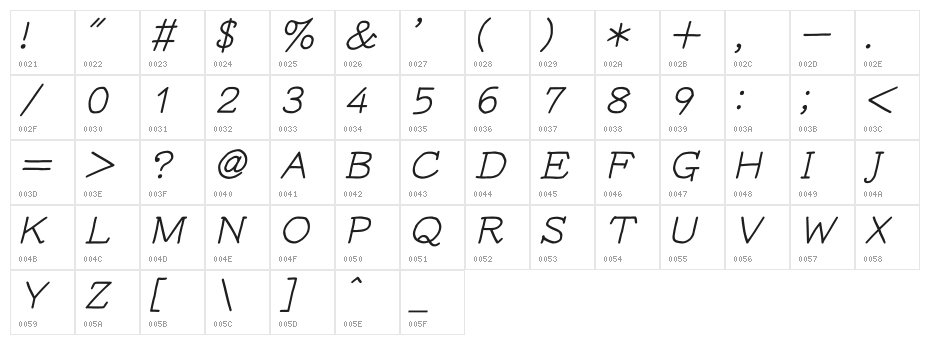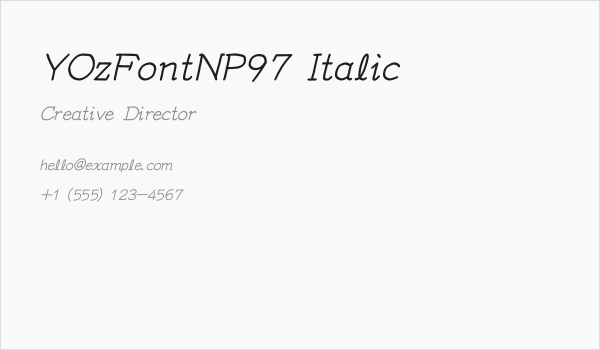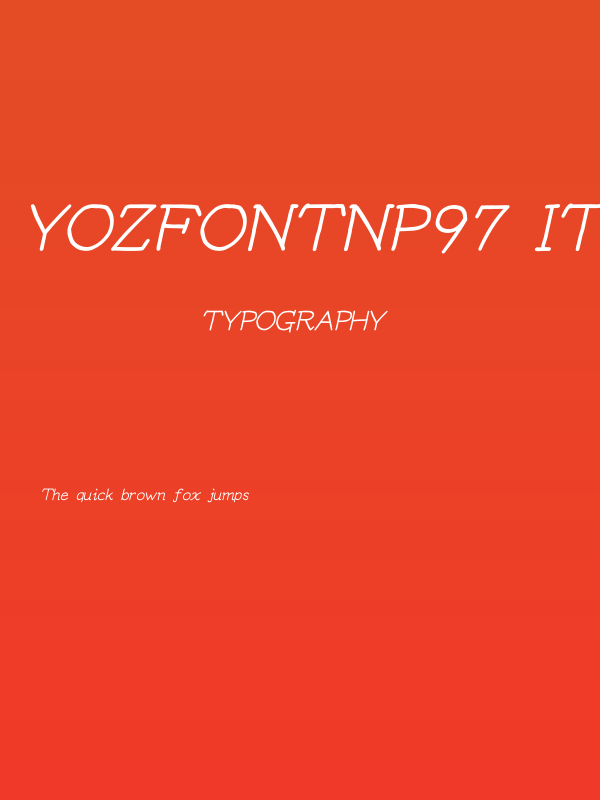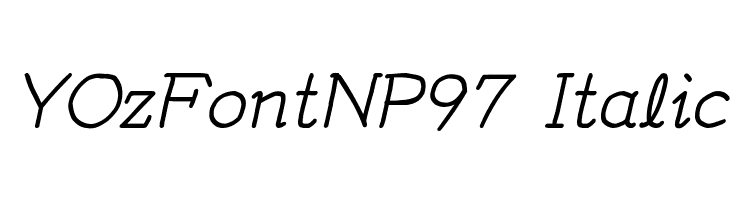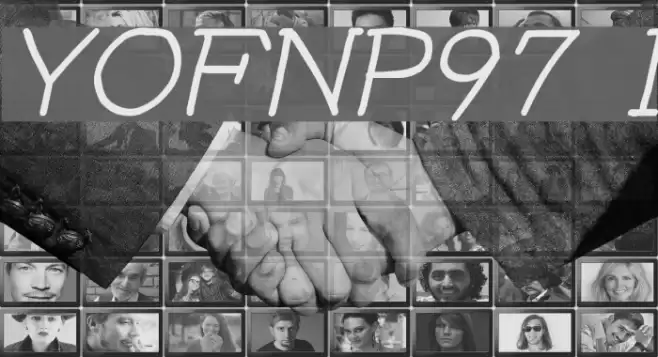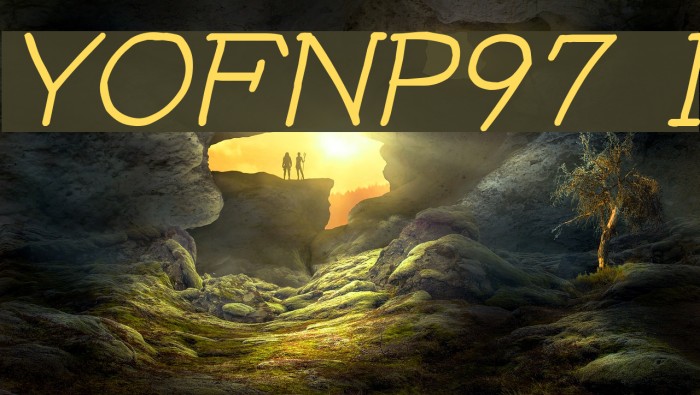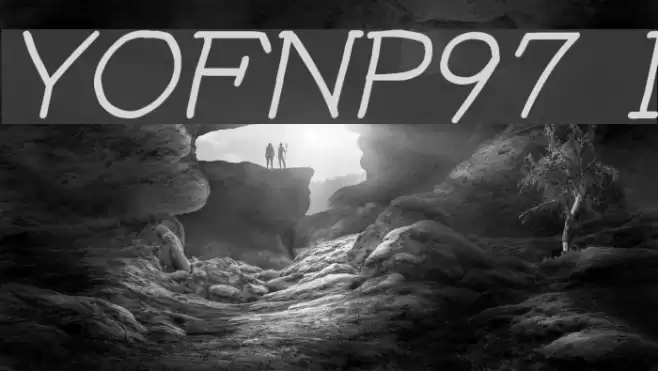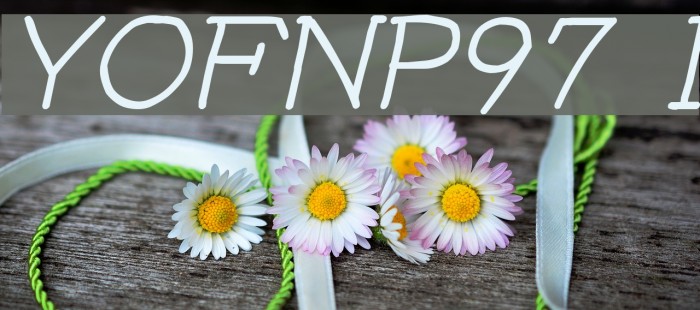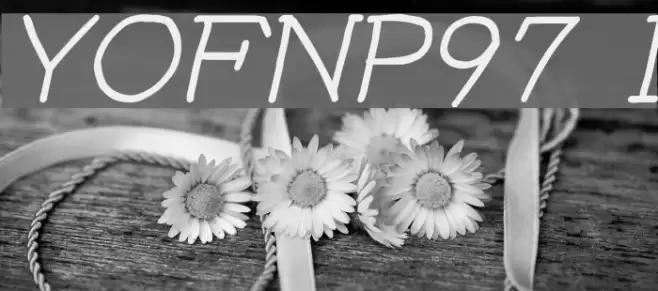
YOzFontNP97 Italic Font
| Gesamtstil | Classic |
| Anwendungsfall | Logos, Invitations, Headlines |
| Vorgeschlagene Projekte | Ideal for projects requiring a touch of elegance, such as wedding invitations, formal event programs, or luxury brand logos. |